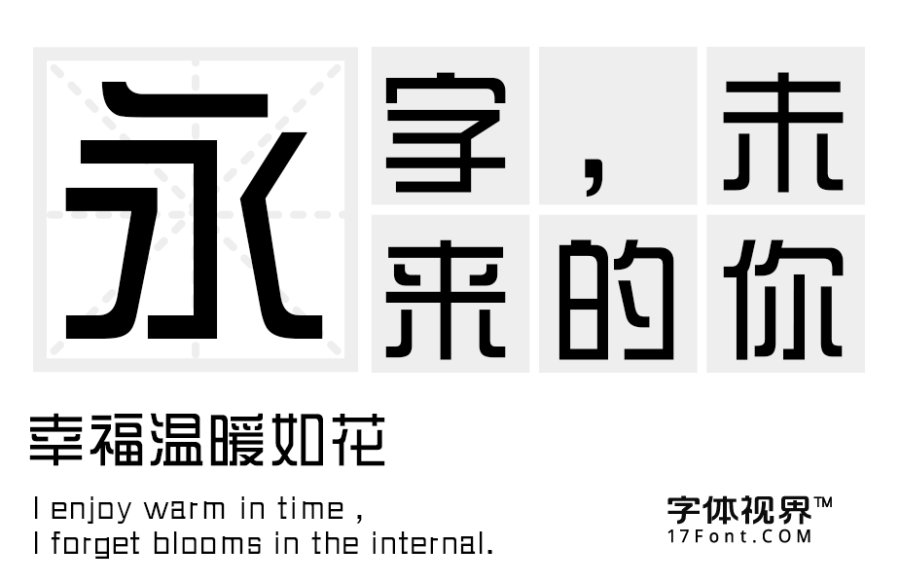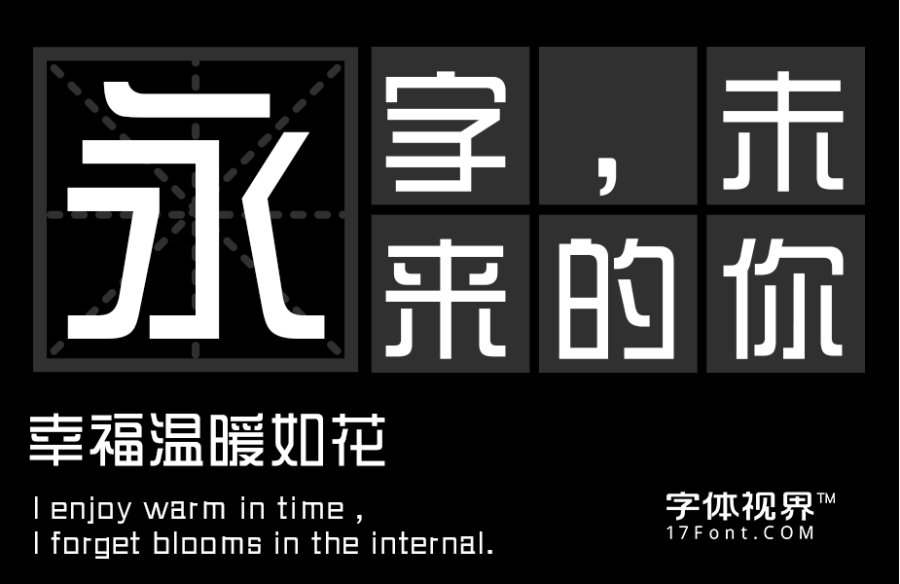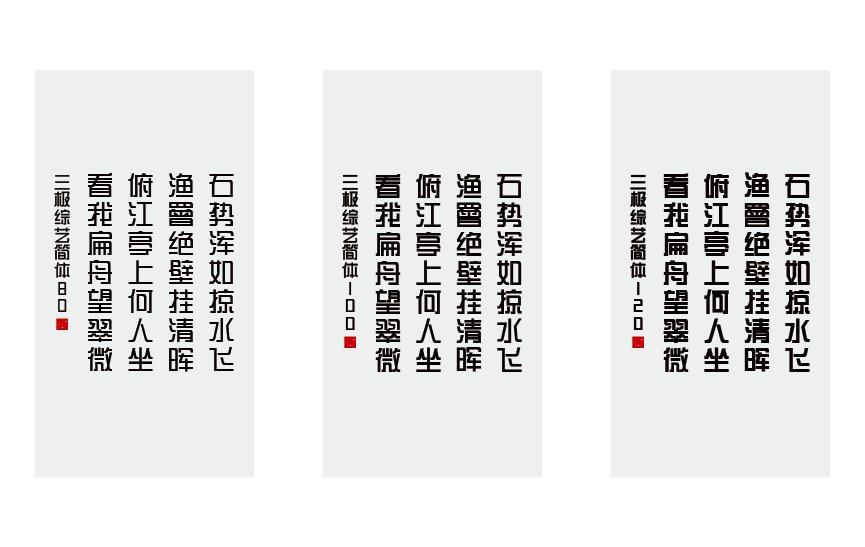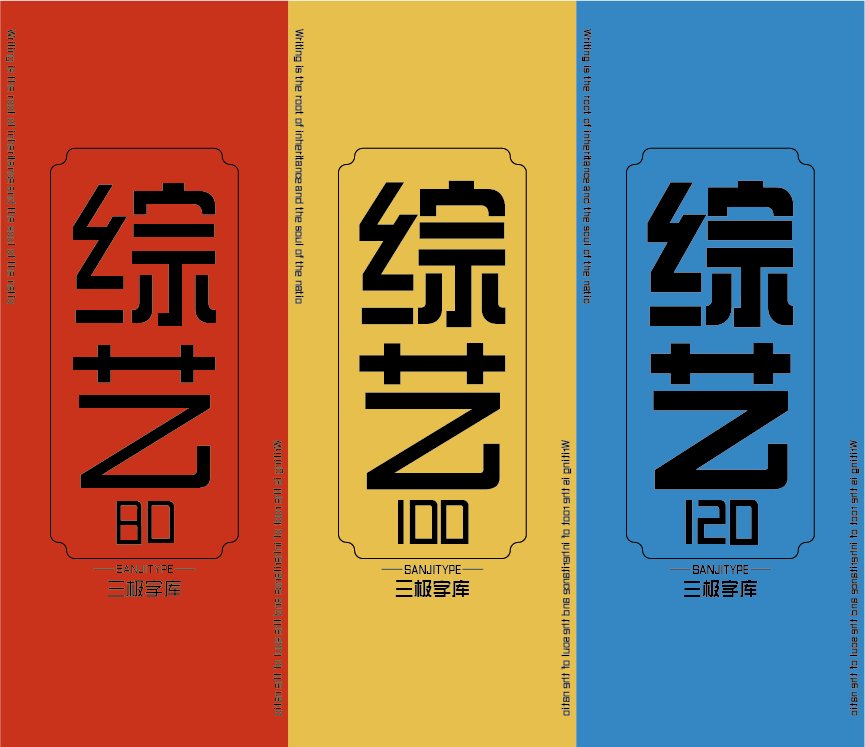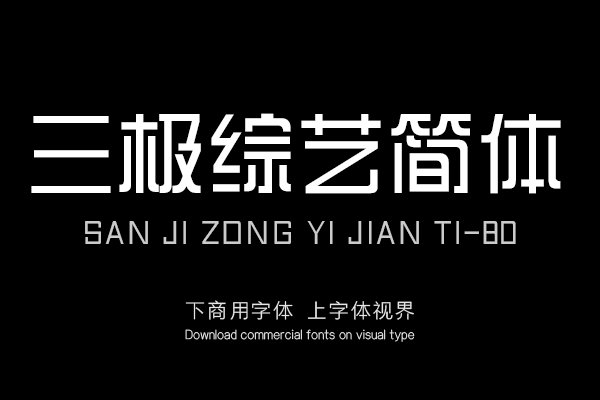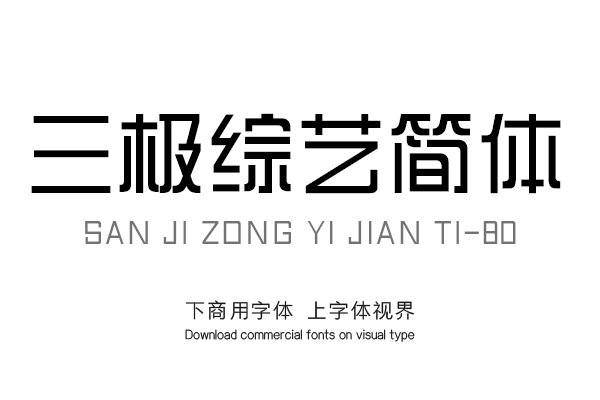
三极综艺简体是一款家族字体,其结构严谨,字型修饰得宜,恰到好处,整体规范而不失特色。严谨秀气而从容和优雅,让人赏心悦目,百看不厌。可广泛用于书刊、广告、包装、店......购买须知:“下载服务费”与“字体VIP”所获得字体 仅用于个人非商用, 商用请联系付费授权。本字体为电脑用字,手机没有root权限不支持直接手机换字(手机如何root,请自行百度搜索教程)。购买前请先 了解清楚后再付款 ,字体为虚拟产品无法回收 一旦购买不支持退款。